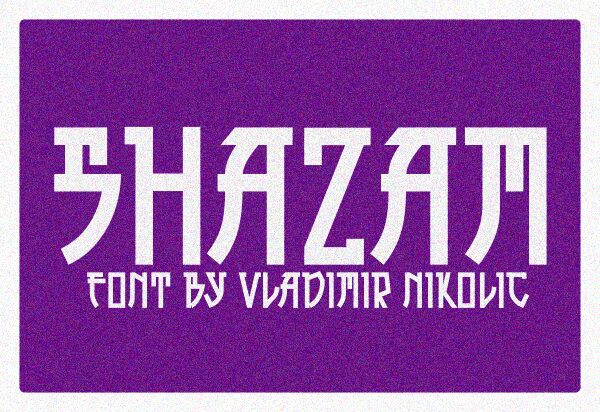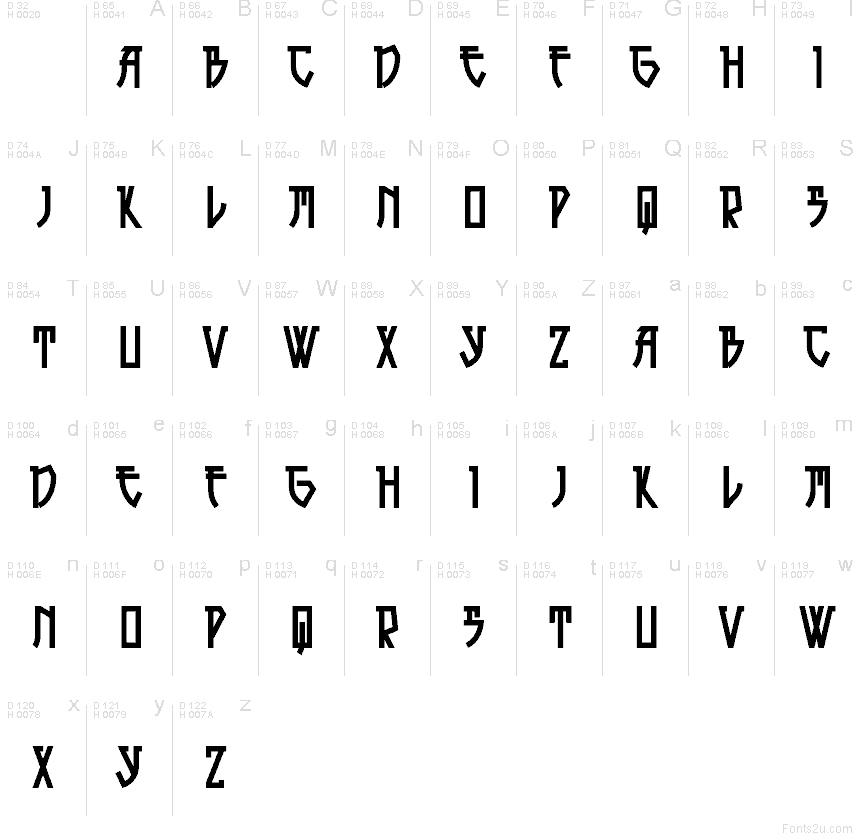
Shazam Flat od Vladimira Nikoliće je bezplatné titulkové písmo v asijském stylu, které má výrazný, plakátový nádech starých vývěsních štítů s jídlem a názvů filmů o bojových uměních. Písmena využívají masivní vertikály, hranaté rohy a ostré diagonální řezy, díky nimž působí celé písmo svižně, kompaktně a lehce retro.
Skvěle zapadne do vizuální identity restaurací, obalů potravin, plakátů na akce, titulků a krátkých log, kde je žádoucí ten známý vzhled asijských nápisů. Jako písmo zdarma se také dobře hodí na titulní strany nebo monogramy, protože pevné, blokové tvary vypadají nejlépe v krátkých textech.
Shazam Flat